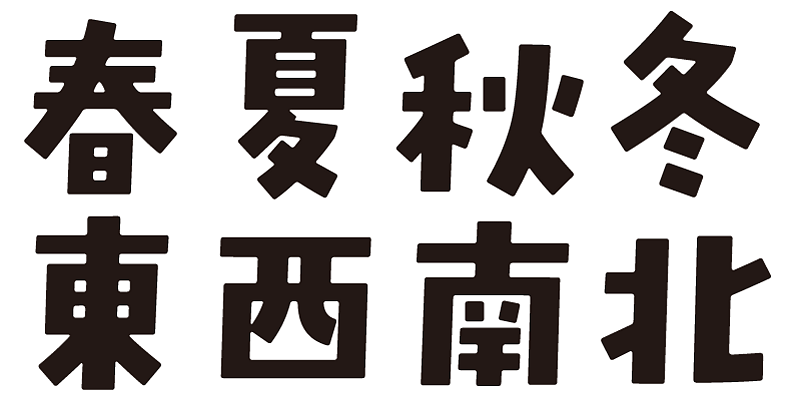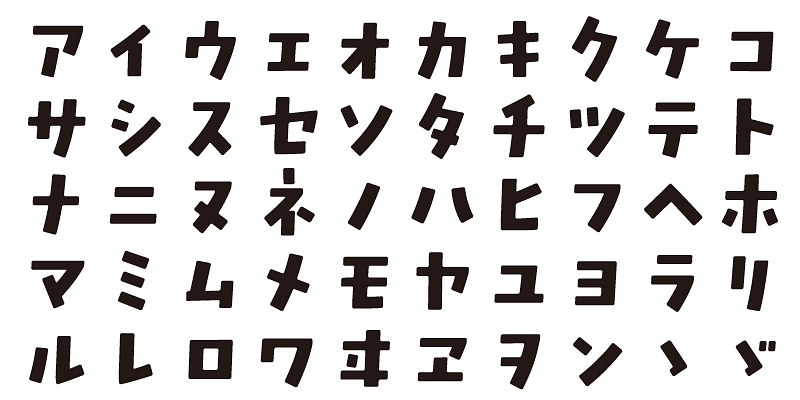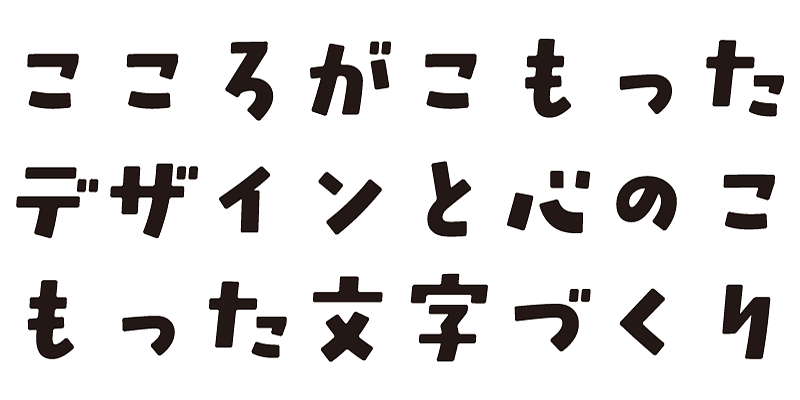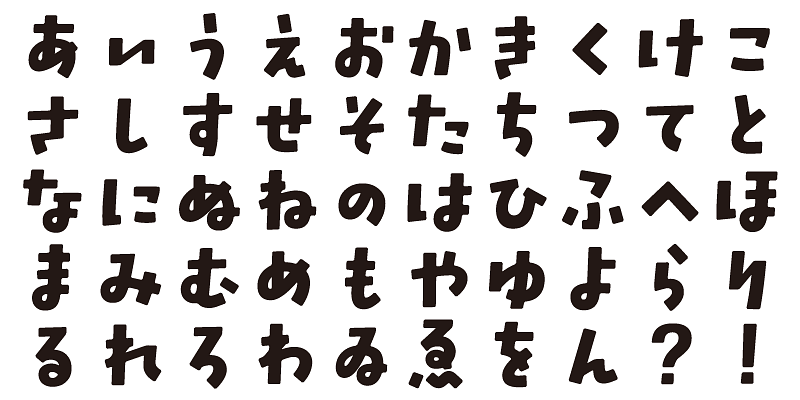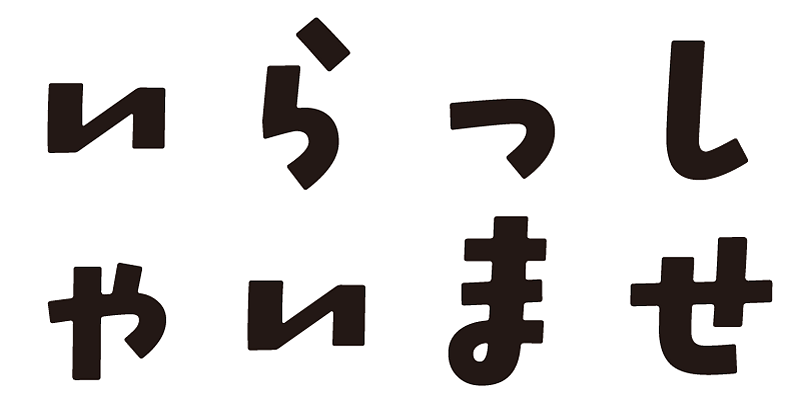
Este tipo de letra tiene un tono brillante y una forma clara, que se combinan con un grosor fuerte y atrevido.
Incluye 1000 caracteres kanji, además de hiragana, katakana, caracteres alfanuméricos y signos de puntuación.
Diseñamos tipos de letra con la esperanza de que añadan un significado subyacente a las palabras escritas. Queremos que el usuario se sienta bien, con comodidad y alegría al utilizar estos tipos de letra.